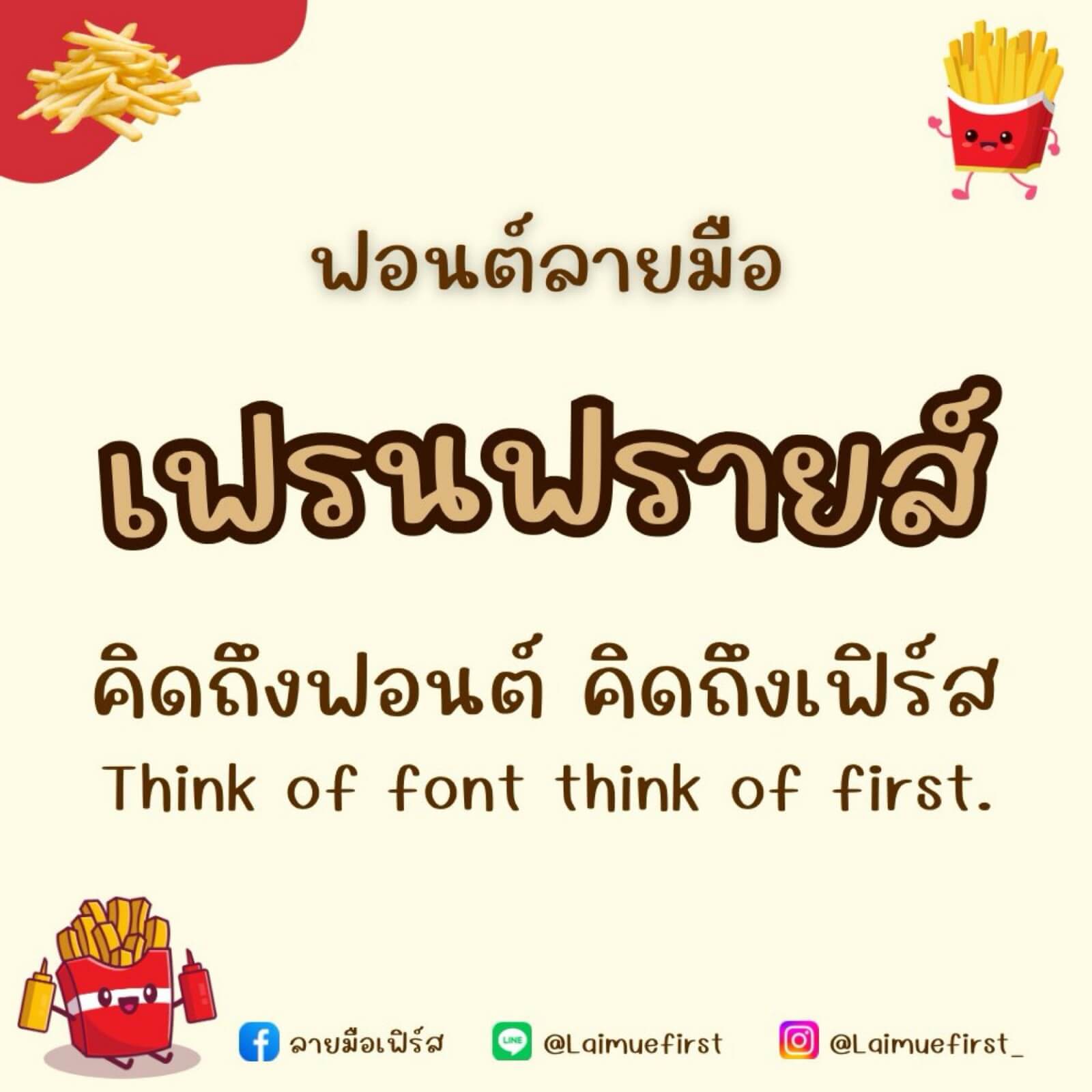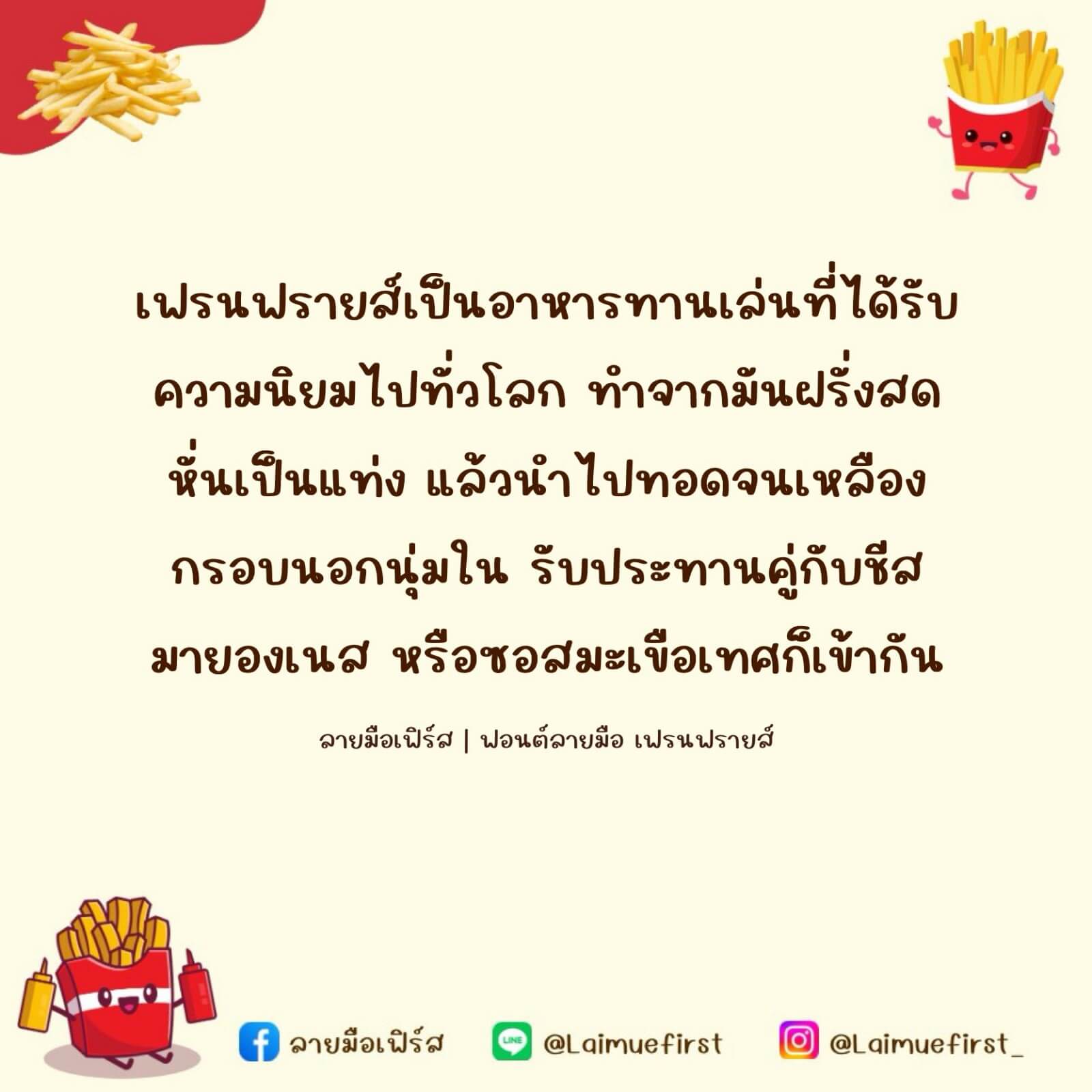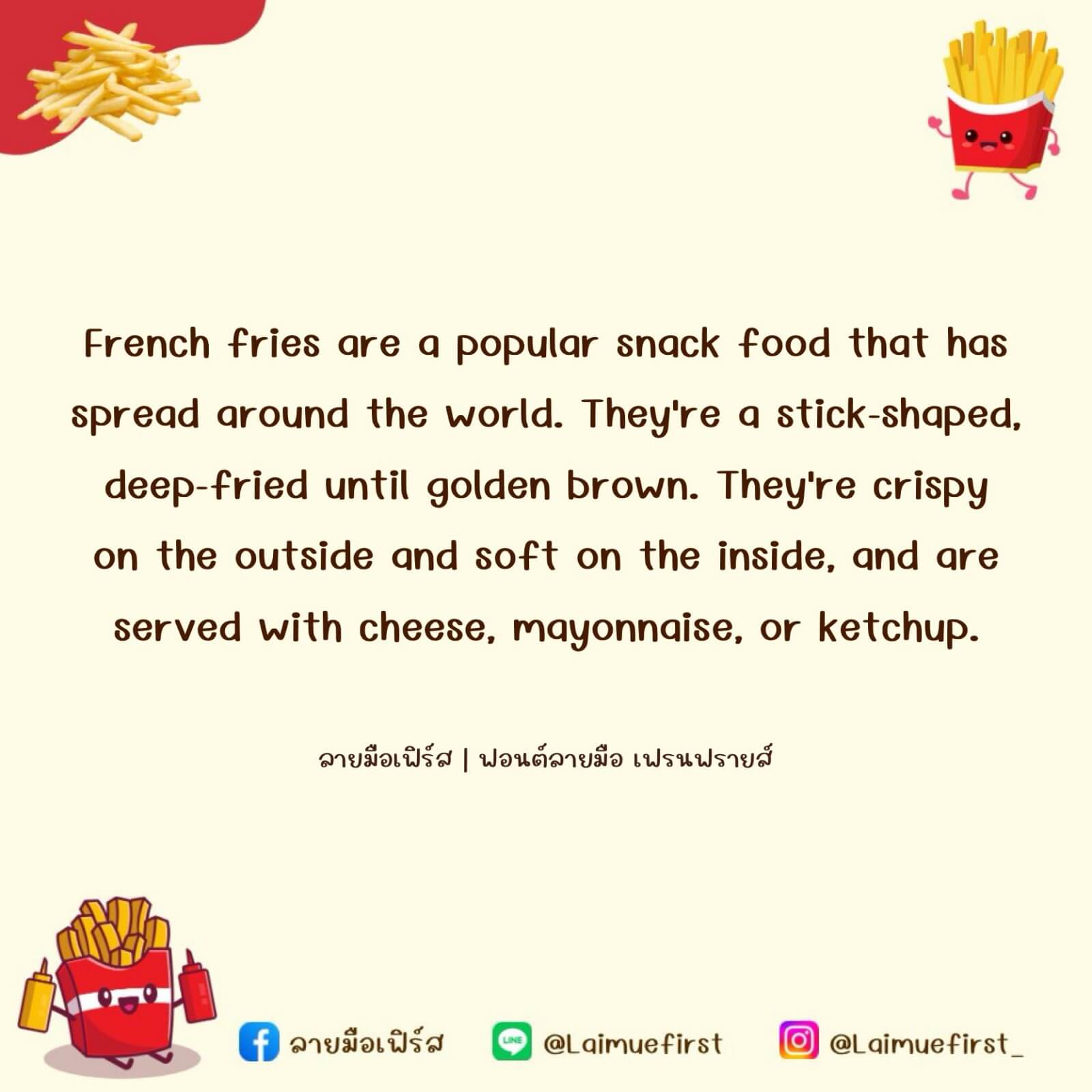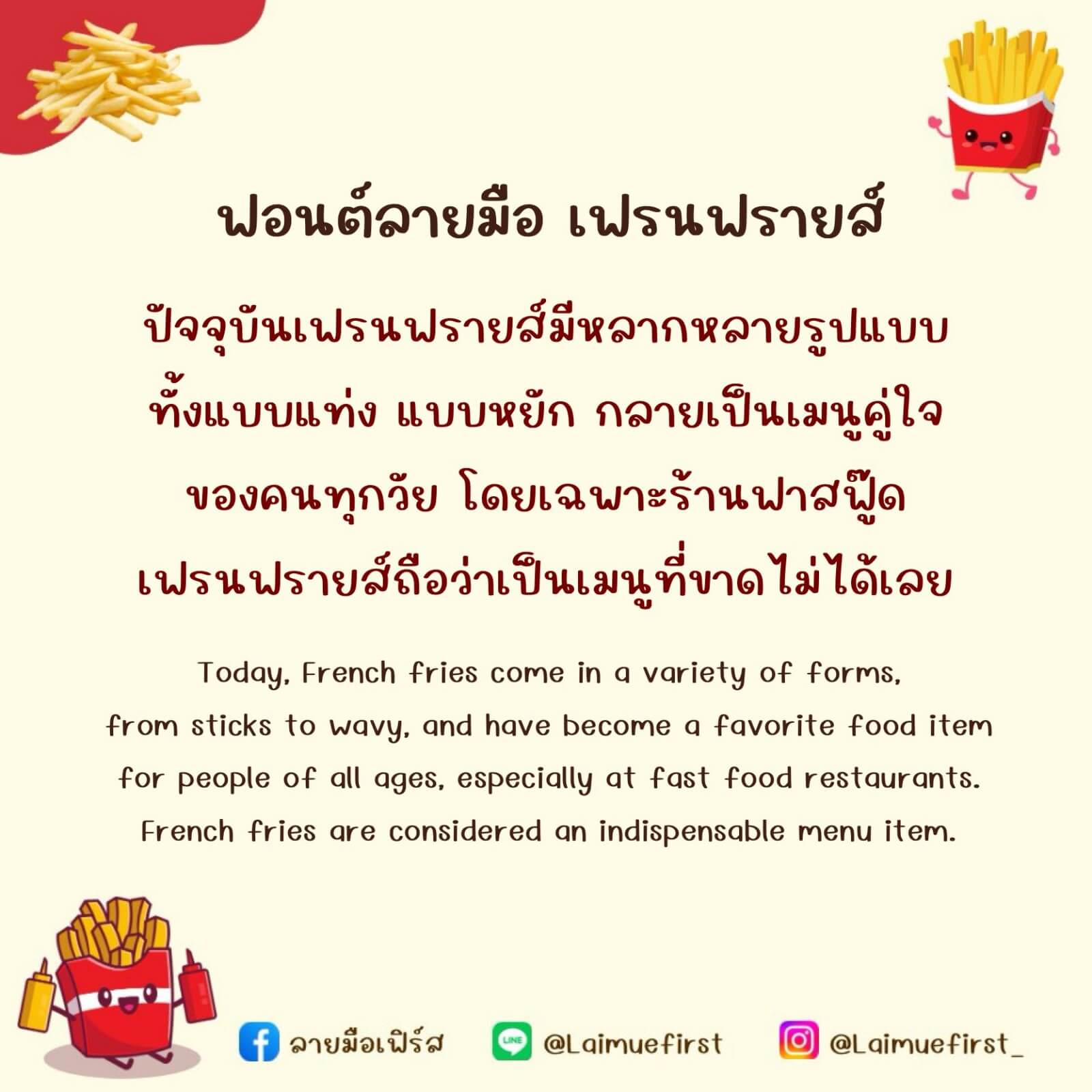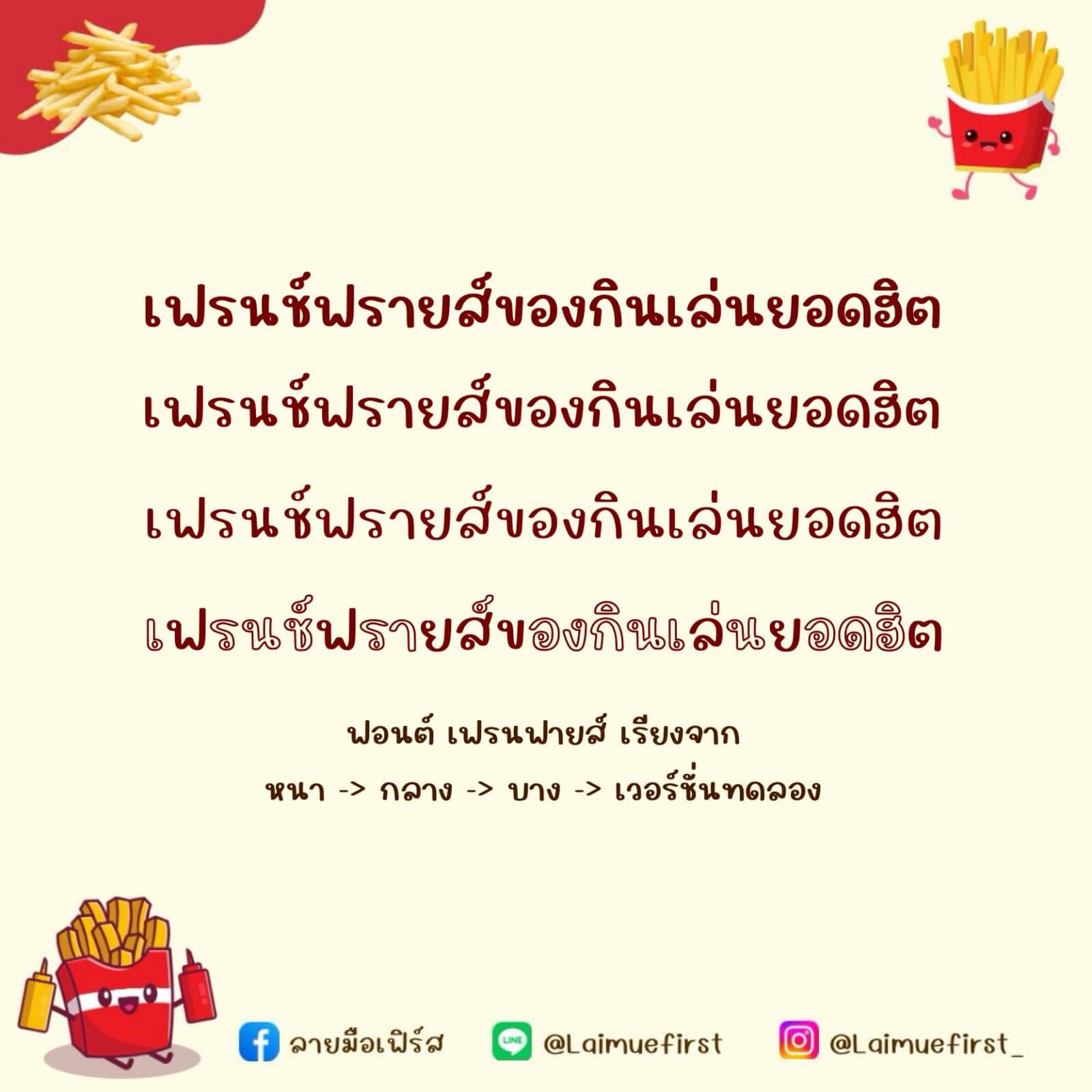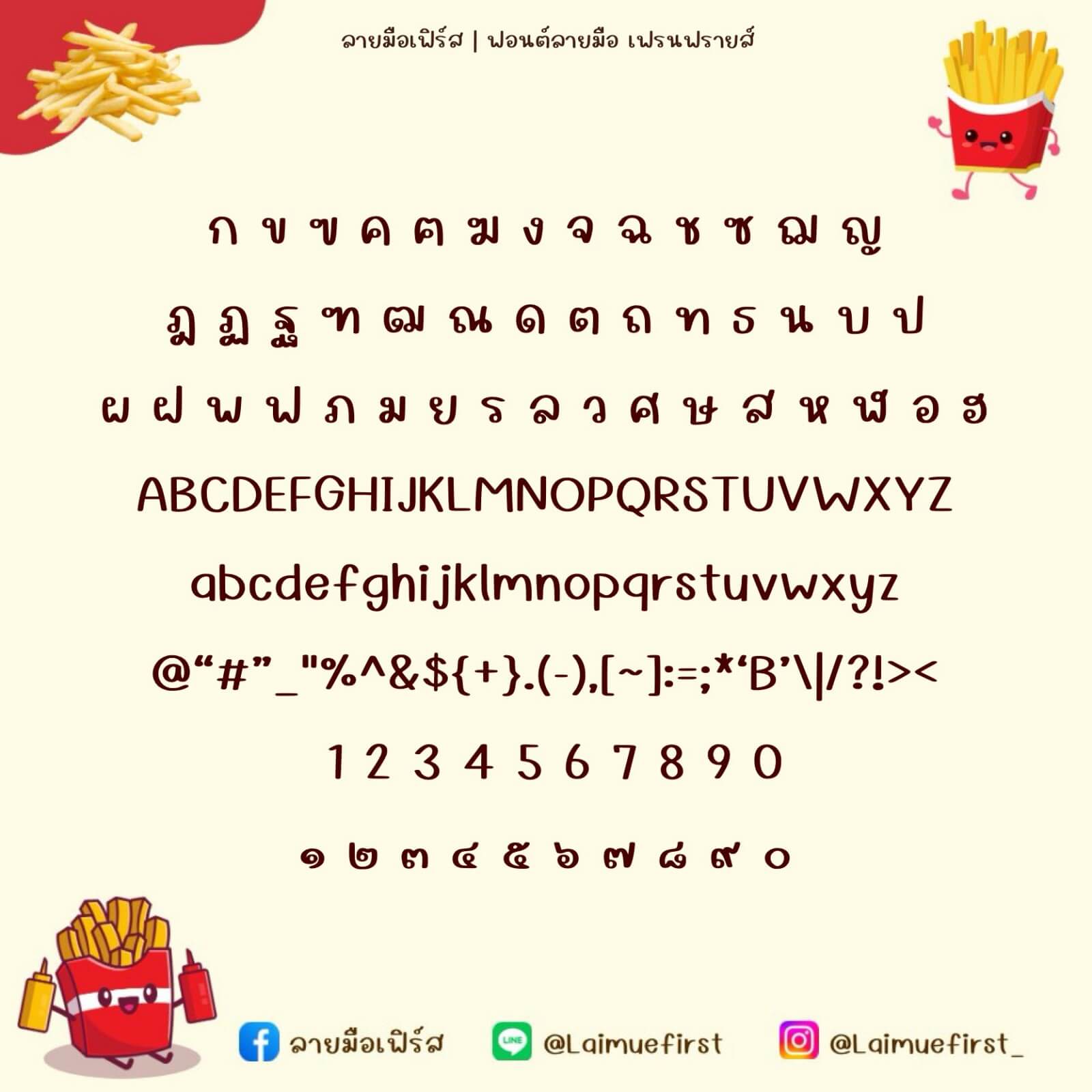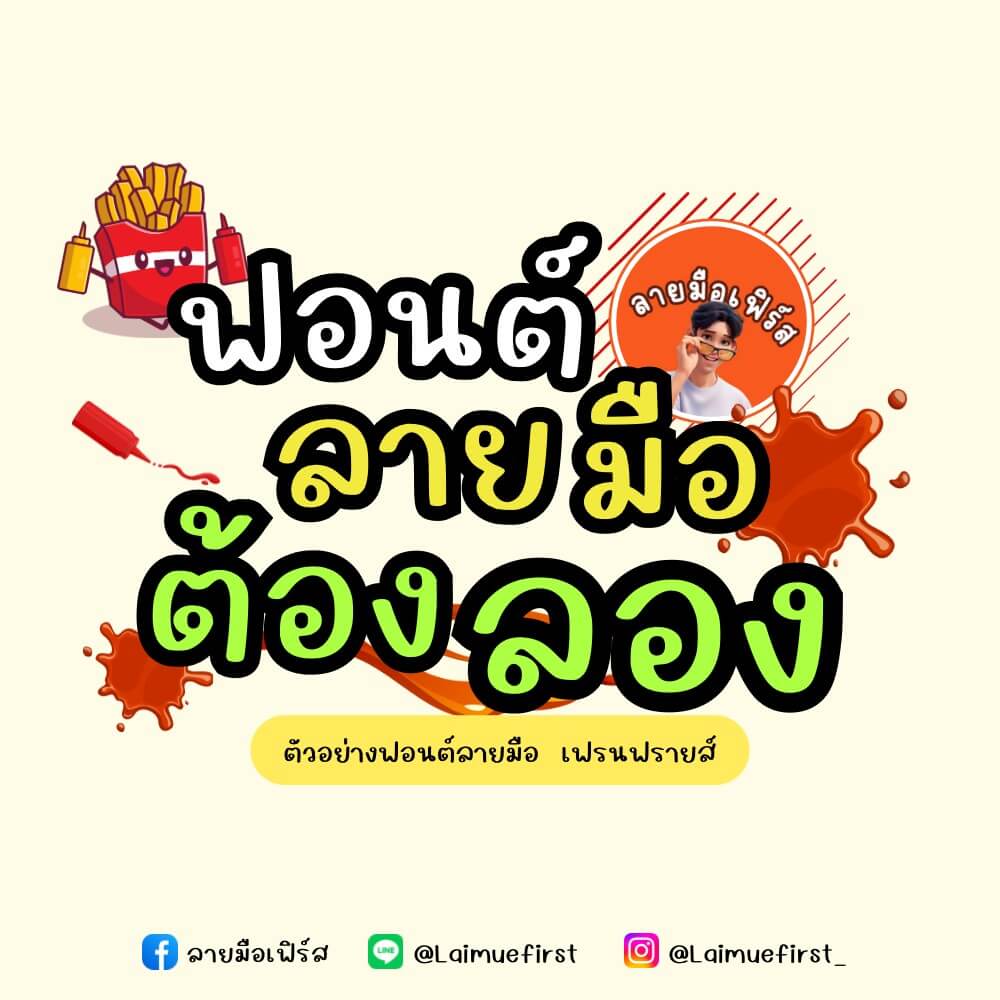
ฟอนต์ลายมือ เฟรนฟายส์ – แจกฟรีสำหรับทดลองใช้งานแบบส่วนตัว เวอร์ชันทดลอง (Demo) ไม่อนุญาตให้นำไปใช้เชิงพาณิชย์นะค้าบบบ
ไฟล์ Demo สำหรับทดลองใช้งาน ตัวอักษรหนา-บางไม่เท่ากัน
โดยฟอนต์เชิงพาณิชย์จะมีไฟล์ฟอนต์ 3 ขนาด (ปกติ/หนา/บาง)